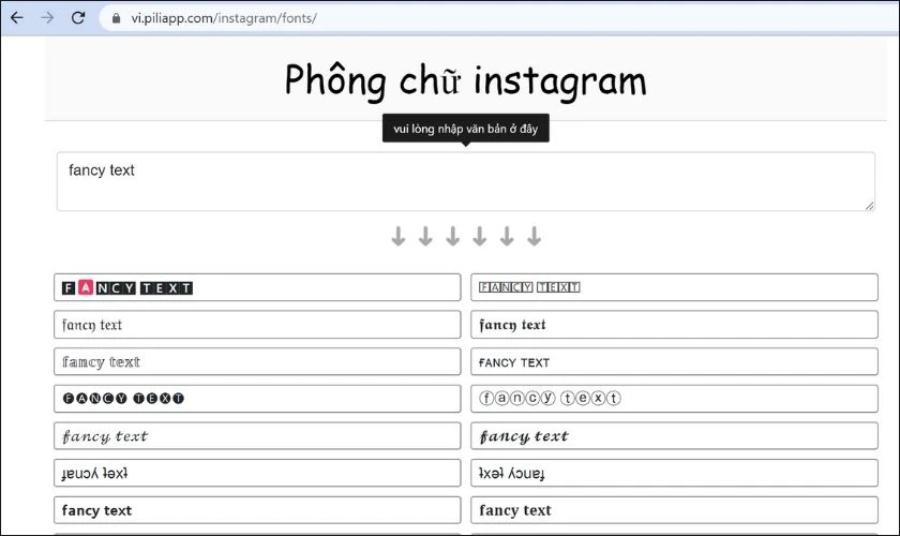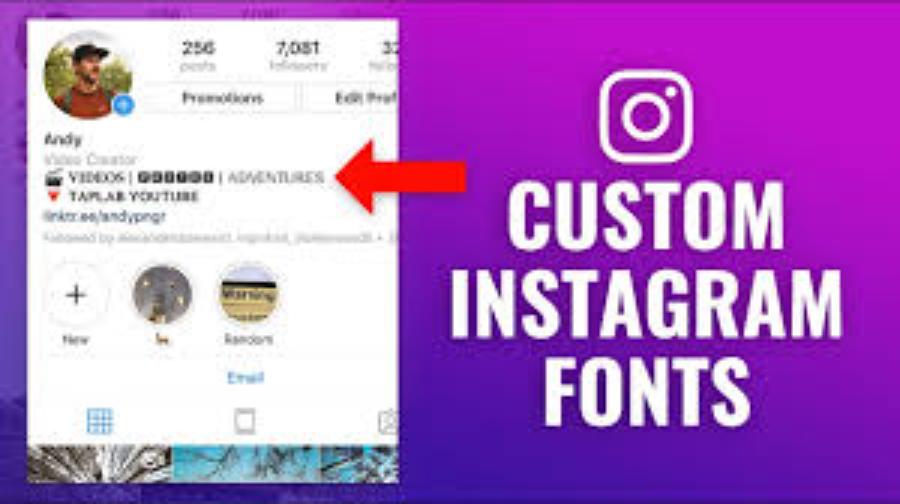
Công cụ đổi font chữ Instagram: Những trang web tạo font chữ Insta đẹp và đơn giản
Khám phá các công cụ đổi font chữ Instagram miễn phí, dễ sử dụng, giúp bạn tạo ra những kiểu chữ độc đáo và thu hút trên hồ sơ và bài đăng của mình.
Việc thay đổi font chữ trên Instagram không chỉ giúp nội dung trở nên nổi bật mà còn thể hiện cá tính riêng của người dùng. Với sự hỗ trợ của các công cụ trực tuyến, việc tạo ra những kiểu chữ độc đáo trở nên dễ dàng hơn bao giờ hết. Bài viết này sẽ giới thiệu đến bạn những trang web tạo font chữ Insta đẹp và đơn giản nhất hiện nay.
1. Font chữ - "Gương mặt" của Instagram
Trong thế giới mạng xã hội đầy màu sắc như Instagram, nơi mà hình ảnh và video chiếm ưu thế, font chữ đôi khi bị bỏ qua. Tuy nhiên, font chữ lại đóng vai trò quan trọng trong việc truyền tải thông điệp, thể hiện cá tính và tạo ấn tượng cho Instagram cá nhân hoặc thương hiệu của bạn. Một font chữ độc đáo và phù hợp có thể giúp bạn nổi bật giữa hàng triệu người dùng khác, thu hút sự chú ý và tạo dấu ấn riêng. Đó là lý do tại sao các công cụ đổi font chữ Instagram ngày càng trở nên phổ biến và được ưa chuộng.
Font chữ trên Instagram đóng vai trò quan trọng như một "gương mặt" đại diện cho thương hiệu, góp phần tạo nên sự nhất quán và nhận diện đặc trưng. Với thiết kế tinh tế, hiện đại và dễ tiếp cận, font chữ không chỉ hỗ trợ truyền tải thông điệp mà còn giúp nâng cao trải nghiệm người dùng. Việc lựa chọn và sử dụng font chữ phù hợp là yếu tố then chốt trong việc xây dựng hình ảnh chuyên nghiệp và thu hút sự chú ý trên nền tảng mạng xã hội này.
2. Tại sao bạn cần công cụ đổi font chữ Instagram?
Công cụ đổi font chữ Instagram là một tiện ích hữu ích giúp bạn tạo ra những nội dung độc đáo và thu hút hơn trên nền tảng mạng xã hội. Việc sử dụng các công cụ đổi font chữ Instagram mang lại nhiều lợi ích đáng kể:
• Tạo sự khác biệt và thu hút sự chú ý: Trong "biển" thông tin và hình ảnh trên Instagram, một font chữ độc đáo sẽ giúp bio, caption, story hay comment của bạn trở nên khác biệt, thu hút ánh nhìn của người xem và khiến họ chú ý đến nội dung bạn muốn truyền tải. Với sự hỗ trợ của công cụ này, bạn có thể thay đổi kiểu chữ để làm nổi bật bài viết, câu chuyện hoặc phần tiểu sử của mình, từ đó tạo ấn tượng mạnh mẽ với người xem.
• Thể hiện cá tính và phong cách riêng: Font chữ là một yếu tố quan trọng trong việc xây dựng hình ảnh cá nhân hoặc thương hiệu. Việc lựa chọn font chữ phù hợp sẽ giúp bạn thể hiện phong cách, cá tính và giọng điệu riêng của mình một cách hiệu quả.
• Nhấn mạnh thông điệp quan trọng: Sử dụng font chữ đặc biệt cho những từ khóa, câu trích dẫn hoặc thông điệp quan trọng trong caption hay story sẽ giúp chúng nổi bật hơn, thu hút sự chú ý của người đọc và truyền tải thông điệp một cách mạnh mẽ hơn.
• Tăng tính thẩm mỹ cho Instagram và bài viết: Một font chữ đẹp và hài hòa với tổng thể Instagram sẽ góp phần nâng cao tính thẩm mỹ, tạo ấn tượng chuyên nghiệp và thu hút người theo dõi mới. Điều này không chỉ giúp tăng tính thẩm mỹ mà còn góp phần xây dựng thương hiệu cá nhân hoặc doanh nghiệp một cách chuyên nghiệp và sáng tạo hơn. Sử dụng các font chữ đa dạng cũng là cách để bạn thể hiện cá tính và phong cách riêng, đồng thời thu hút thêm sự chú ý từ cộng đồng người theo dõi.
3. Nhược điểm của việc đổi font chữ Instagram trực tiếp
Instagram hiện tại không cung cấp tùy chọn thay đổi font chữ trực tiếp trong ứng dụng. Người dùng bị giới hạn trong một vài font chữ mặc định. Điều này có nghĩa là để có được những font chữ độc đáo và cá tính hơn, bạn bắt buộc phải sử dụng các công cụ hoặc trang web của bên thứ ba để tạo ra văn bản với font chữ mong muốn và sau đó sao chép, dán vào Instagram. Đây chính là lý do sự ra đời và phát triển của các công cụ đổi font chữ Instagram.
Việc đổi font chữ trực tiếp trên Instagram có thể mang lại một số nhược điểm đáng lưu ý. Trước tiên, không phải tất cả các font chữ đều được hỗ trợ trên mọi thiết bị hoặc nền tảng, dẫn đến tình trạng hiển thị không đồng nhất. Điều này có thể gây khó khăn trong việc truyền tải thông điệp hoặc làm giảm tính chuyên nghiệp của nội dung. Thêm vào đó, việc sử dụng các font chữ quá phức tạp hoặc khó đọc có thể ảnh hưởng đến trải nghiệm người dùng, đặc biệt là khi họ cần nhanh chóng nắm bắt thông tin. Ngoài ra, việc thay đổi font chữ không đúng cách có thể làm giảm khả năng tối ưu hóa nội dung trên công cụ tìm kiếm (SEO), từ đó ảnh hưởng đến khả năng tiếp cận đối tượng mục tiêu. Vì vậy, cần cân nhắc kỹ lưỡng khi áp dụng các thay đổi này để đảm bảo hiệu quả và tính nhất quán trong việc xây dựng thương hiệu cá nhân hoặc doanh nghiệp.
4. Giới thiệu các loại font chữ Instagram độc đáo và phổ biến
Các công cụ đổi font chữ Instagram thường cung cấp rất nhiều kiểu chữ độc đáo, từ những font chữ thanh lịch, cổ điển đến những font chữ vui nhộn, cá tính. Một số loại font chữ phổ biến có thể kể đến như font chữ viết tay mềm mại, thể hiện sự thân thiện và gần gũi; font chữ đậm và góc cạnh, mang phong cách hiện đại và mạnh mẽ; hoặc các font chữ cách điệu với ký tự đặc biệt, tạo sự phá cách và thu hút sự chú ý. Một số loại font chữ Instagram phổ biến và được yêu thích bao gồm:
• Font chữ in nghiêng (Italic): Tạo cảm giác mềm mại, nghệ thuật.
• Font chữ in đậm (Bold): Nhấn mạnh và thu hút sự chú ý.
• Font chữ gạch chân (Underline): Thường dùng để đánh dấu hoặc liên kết.
• Font chữ bong bóng (Bubble Text): Tạo vẻ ngoài trẻ trung, năng động.
• Font chữ gothic: Mang đậm phong cách cổ điển, huyền bí.
• Font chữ serif và sans-serif cách điệu: Những biến thể độc đáo của các kiểu chữ cơ bản.
• Font chữ viết tay (Script): Tạo cảm giác cá nhân, thân mật.
• Các ký tự đặc biệt và biểu tượng: Thường được kết hợp để tạo điểm nhấn độc đáo.
Để sử dụng, bạn có thể tìm đến các công cụ chuyển đổi font trực tuyến hoặc ứng dụng hỗ trợ chỉnh sửa văn bản dành riêng cho Instagram. Việc lựa chọn font chữ phù hợp sẽ giúp bạn tối ưu hóa hiệu quả truyền tải thông điệp và tạo ấn tượng mạnh mẽ với người xem. Việc khám phá và lựa chọn font chữ phù hợp sẽ giúp bạn truyền tải đúng thông điệp và thể hiện phong cách riêng của mình trên Instagram.
5. Top 5+ trang web/công cụ đổi font chữ Instagram đẹp và đơn giản nhất
Dưới đây là danh sách những trang web và công cụ đổi font chữ Instagram được nhiều người yêu thích vì sự tiện lợi và đa dạng của chúng:
5.1. LingoJam (lingojam.com):
• LingoJam (lingojam.com) là một nền tảng trực tuyến cho phép người dùng tạo và tùy chỉnh các công cụ chuyển đổi văn bản thành các định dạng khác nhau một cách dễ dàng. Với giao diện thân thiện và tính năng đa dạng, LingoJam hỗ trợ người dùng thiết kế các bộ chuyển đổi ngôn ngữ, ký tự đặc biệt hoặc các kiểu văn bản độc đáo phục vụ cho nhiều mục đích khác nhau, từ sáng tạo nội dung đến nghiên cứu ngôn ngữ. Đây là một công cụ hữu ích cho cả cá nhân và tổ chức muốn tối ưu hóa việc truyền tải thông điệp một cách hiệu quả và sáng tạo.
• Ưu điểm: Giao diện đơn giản, dễ sử dụng, cung cấp nhiều kiểu chữ độc đáo.
• Cách sử dụng: Truy cập trang web, nhập văn bản vào ô bên trái, các font chữ được tạo sẽ hiển thị ở ô bên phải. Sao chép font chữ bạn thích.
5.2. Instagram Fonts (instagramfonts.io):
• Instagram Fonts (instagramfonts.io) là một công cụ trực tuyến hữu ích, cho phép người dùng tạo ra các kiểu chữ độc đáo và sáng tạo để sử dụng trên nền tảng Instagram. Với giao diện thân thiện và dễ sử dụng, công cụ này giúp người dùng tùy chỉnh văn bản theo nhiều phong cách khác nhau, từ thanh lịch, hiện đại đến phá cách và nghệ thuật. Đây là một giải pháp lý tưởng cho những ai muốn làm nổi bật nội dung của mình, thu hút sự chú ý và tăng tính chuyên nghiệp trong việc xây dựng thương hiệu cá nhân hoặc doanh nghiệp trên mạng xã hội.
• Ưu điểm: Giao diện thân thiện, tốc độ tạo font nhanh chóng, nhiều lựa chọn font chữ đẹp.
• Cách sử dụng: Truy cập trang web, nhập văn bản, chọn font chữ từ danh sách và sao chép.
5.3. FontGet
• FontGet là một công cụ hữu ích giúp người dùng truy cập và quản lý các phông chữ một cách dễ dàng và hiệu quả. Với khả năng cung cấp nhiều lựa chọn phông chữ đa dạng, FontGet hỗ trợ tạo nên sự sáng tạo và chuyên nghiệp trong thiết kế đồ họa, tài liệu, hoặc bất kỳ dự án nào yêu cầu tính thẩm mỹ cao. Công cụ này không chỉ giúp tiết kiệm thời gian mà còn đảm bảo chất lượng, đáp ứng nhu cầu của cả những nhà thiết kế khó tính nhất!
• Ưu điểm: Đa dạng font chữ, có thể xem trước font chữ trực tiếp.
• Cách sử dụng: Truy cập trang web, nhập văn bản, duyệt qua các font và sao chép font bạn muốn.
5.4. CoolSymbol:
• CoolSymbol là một công cụ trực tuyến hữu ích, cung cấp nhiều biểu tượng độc đáo, ký tự đặc biệt và font chữ đẹp mắt, giúp người dùng dễ dàng tạo ra các nội dung sáng tạo và thu hút. Với giao diện thân thiện và tính năng đa dạng, CoolSymbol hỗ trợ việc thiết kế các bài viết, tin nhắn hay tài liệu chuyên nghiệp, đồng thời mang lại sự khác biệt và ấn tượng trong giao tiếp trực tuyến. Công cụ này không chỉ phù hợp cho cá nhân mà còn là một giải pháp hiệu quả cho các doanh nghiệp muốn tạo điểm nhấn trong chiến lược truyền thông của mình.
• Ưu điểm: Rất nhiều lựa chọn, có thể kết hợp font chữ với ký tự đặc biệt.
• Cách sử dụng: Truy cập trang web, nhập văn bản, chọn font và ký tự bạn thích, sau đó sao chép.
5.5. IGFonts.io (igfonts.io):
• IGFonts.io (igfonts.io) là một công cụ trực tuyến hữu ích, chuyên cung cấp các kiểu chữ độc đáo và sáng tạo dành cho người dùng Instagram. Với giao diện thân thiện và dễ sử dụng, người dùng có thể nhanh chóng tạo ra các kiểu chữ phong cách để làm nổi bật bài đăng, tiểu sử hoặc câu chuyện trên nền tảng mạng xã hội này. IGFonts.io hỗ trợ nhiều tùy chọn phông chữ khác nhau, từ đơn giản đến phức tạp, giúp người dùng thể hiện cá tính và sự chuyên nghiệp trong từng nội dung. Công cụ này không chỉ phù hợp với cá nhân mà còn là giải pháp hiệu quả cho các doanh nghiệp muốn tạo dấu ấn thương hiệu trên Instagram.
• Ưu điểm: Dễ sử dụng trên cả máy tính và điện thoại.
• Cách sử dụng: Truy cập trang web, nhập văn bản và chọn font chữ để sao chép.
6. Hướng dẫn chi tiết cách sử dụng công cụ đổi font chữ Instagram
Quy trình sử dụng các công cụ đổi font chữ Instagram thường rất đơn giản và tương tự nhau:
• Bước 1: Truy cập trang web/ứng dụng: Mở trình duyệt web trên điện thoại hoặc máy tính và truy cập một trong các trang web được liệt kê ở trên, hoặc mở ứng dụng Stylish Text nếu bạn đã tải về.
• Bước 2: Nhập văn bản bạn muốn đổi font: Tìm ô nhập văn bản (thường có dòng chữ "Enter your text here" hoặc tương tự) và gõ hoặc dán đoạn văn bản bạn muốn thay đổi font chữ.
• Bước 3: Chọn font chữ yêu thích: Trang web/ứng dụng sẽ tự động tạo ra nhiều kiểu font chữ khác nhau từ văn bản bạn vừa nhập. Duyệt qua danh sách và chọn font chữ mà bạn ưng ý nhất.
• Bước 4: Sao chép font chữ đã tạo: Nhấp vào nút "Copy" (Sao chép) hoặc chọn và sao chép thủ công đoạn văn bản với font chữ bạn đã chọn.
• Bước 5: Dán vào bio, caption, story hoặc comment trên Instagram: Mở ứng dụng Instagram, truy cập vào phần bạn muốn sử dụng font chữ mới (chỉnh sửa Instagram, tạo bài viết mới, story hoặc bình luận) và dán đoạn văn bản đã sao chép vào ô tương ứng.
Lưu ý rằng việc sử dụng font chữ độc đáo có thể giúp nội dung của bạn nổi bật hơn, nhưng cần đảm bảo tính dễ đọc và phù hợp với đối tượng mà bạn muốn hướng đến.
7. Lưu ý quan trọng khi sử dụng font chữ đặc biệt trên Instagram
Khi sử dụng font chữ đặc biệt trên Instagram, bạn cần lưu ý một số điểm quan trọng để đảm bảo nội dung của mình được trình bày chuyên nghiệp và hiệu quả. Mặc dù việc sử dụng font chữ đặc biệt có thể giúp bạn nổi bật, nhưng cũng có một vài lưu ý quan trọng bạn cần ghi nhớ:
• Tính tương thích của font chữ trên các thiết bị khác nhau: Một số font chữ đặc biệt có thể không hiển thị đúng trên tất cả các thiết bị hoặc hệ điều hành khác nhau. Hãy kiểm tra kỹ trên nhiều thiết bị nếu có thể để đảm bảo người xem nào cũng thấy được font chữ bạn muốn.
• Đọc hiểu và tránh sử dụng font chữ quá phức tạp: Lựa chọn những font chữ dễ đọc và rõ ràng. Tránh sử dụng những font chữ quá cầu kỳ hoặc khó nhìn, có thể gây khó chịu cho người đọc.
• Sử dụng font chữ nhất quán để tạo sự chuyên nghiệp: Nếu bạn là một thương hiệu hoặc muốn xây dựng hình ảnh chuyên nghiệp, hãy cố gắng sử dụng một hoặc một vài font chữ nhất quán trên toàn bộ Instagram và bài viết của mình.
• Cân nhắc về mục đích và đối tượng khi chọn font chữ: Lựa chọn font chữ phù hợp với nội dung bạn muốn truyền tải và đối tượng mục tiêu của bạn. Một font chữ vui nhộn có thể phù hợp với bài đăng cá nhân, nhưng có thể không phù hợp với một thương hiệu nghiêm túc.
• Ngoài ra, hãy kiểm tra khả năng hiển thị của font chữ trên các thiết bị khác nhau, vì một số font đặc biệt có thể không hiển thị đúng trên tất cả các nền tảng hoặc hệ điều hành. Cuối cùng, hãy sử dụng font chữ đặc biệt một cách vừa phải, tránh lạm dụng, để không làm giảm tính chuyên nghiệp và dễ đọc của nội dung. Điều quan trọng nhất là đảm bảo rằng thông điệp của bạn truyền tải một cách rõ ràng, hấp dẫn và tạo ấn tượng tích cực với người xem.
8. Câu hỏi thường gặp về công cụ đổi font chữ Instagram (FAQ)
Công cụ đổi font chữ Instagram là một tiện ích hữu ích giúp người dùng tạo phong cách riêng biệt và thu hút sự chú ý trên mạng xã hội. Bằng cách cung cấp nhiều kiểu chữ độc đáo, công cụ này cho phép bạn tùy chỉnh nội dung bài viết, tiểu sử hoặc bình luận một cách sáng tạo và chuyên nghiệp.
• Việc sử dụng công cụ đổi font chữ Instagram có vi phạm điều khoản của Instagram không? Hầu hết các công cụ này hoạt động dựa trên việc tạo ra các ký tự Unicode đặc biệt, vốn được Instagram hỗ trợ hiển thị. Do đó, việc sử dụng chúng thường không bị coi là vi phạm điều khoản. Tuy nhiên, bạn nên tránh sử dụng các công cụ hoặc phương pháp can thiệp sâu vào hệ thống của Instagram.
• Font chữ đặc biệt có hiển thị trên tất cả các thiết bị không? Như đã đề cập ở trên, khả năng hiển thị có thể khác nhau tùy thuộc vào thiết bị và hệ điều hành.